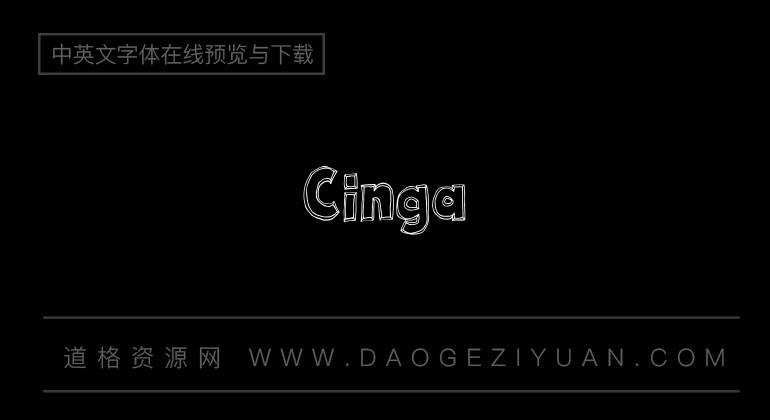
Cinga 是一款美式英文字体,由著名设计师 David Jonathan Ross 于 2018 年设计。它是一款抽象的、充满活力的字体,拥有多种不同的字形和粗细程度,可以满足各式各样的设计需求。Cinga 字体拥有丰富的字符集,可以支持多种语言,比如英文、法文、德文、西班牙文等。它的设计灵感来源于 Art Deco 和现代主义,在细节上也经过精心调整,使其具备更好的可读性和视觉效果。内容介绍
Cinga是一款非常不错的手写艺术字体,具有很好的视觉感,适合于文化类的宣传设计、商业类品牌的广告和产品包装设计以及个性化文字排版等较多场景。